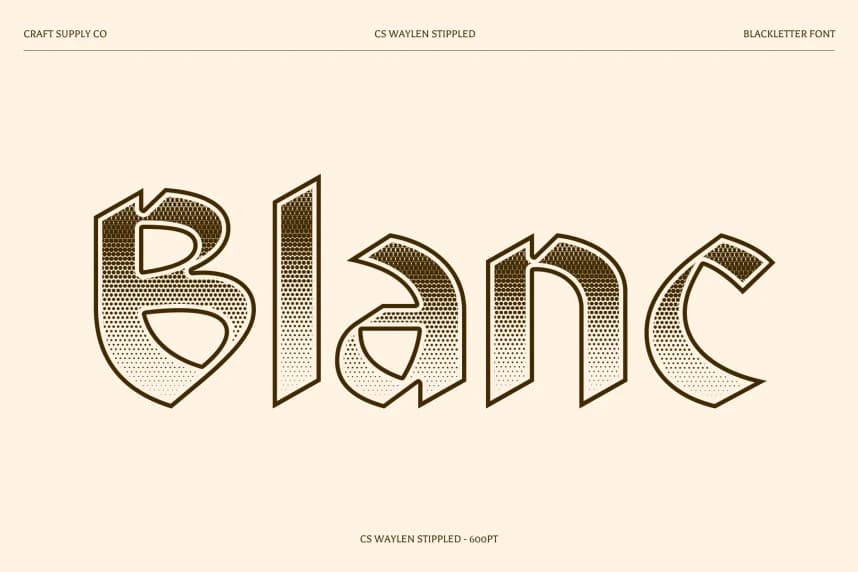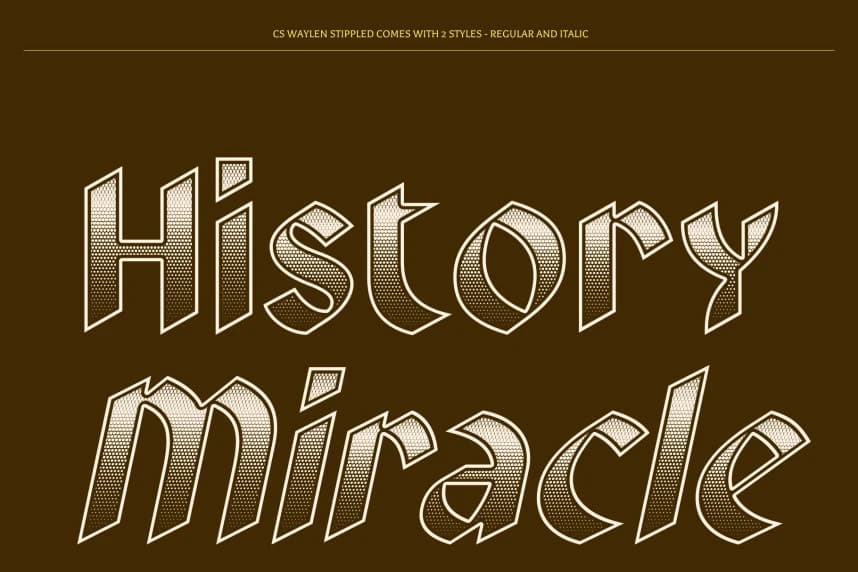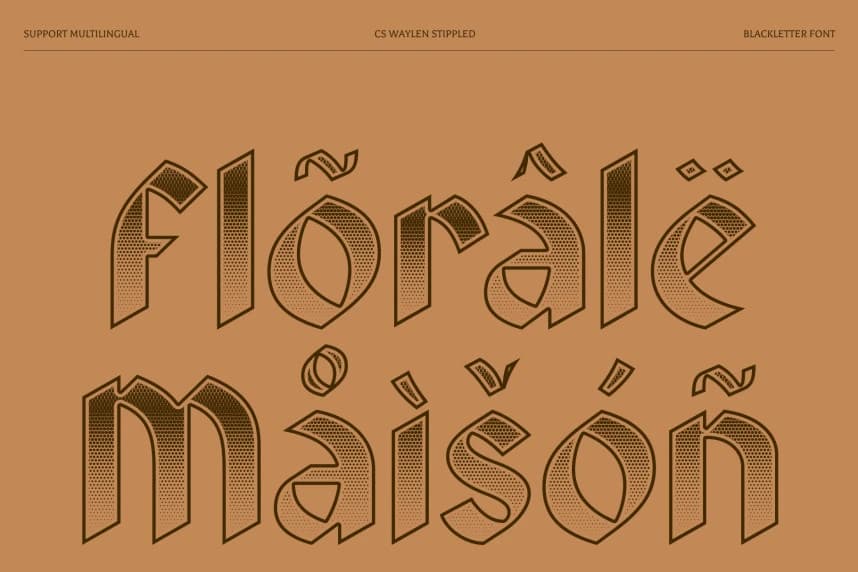
CS Waylen Stippled Font
CS Waylen Stippled Font – Blackletter Yazı Tipi, Bold Dokulu Geleneksel Blackletter Stiliyle Stippleli Derinlik. Bu, geleneksel Gotik tipografinin dramatik karakterini yakalayan güçlü bir Blackletter gösteri yazı tipidir.
CS Waylen Stippled Font – Blackletter Font ile Kalın Dokulu Geleneksel Bold Blackletter Tarzı Stippled Derinlik ile. Bu, geleneksel Gotik tipografinin dramatik karakterini yakalayan güçlü bir Blackletter gösterim yazı tipidir.